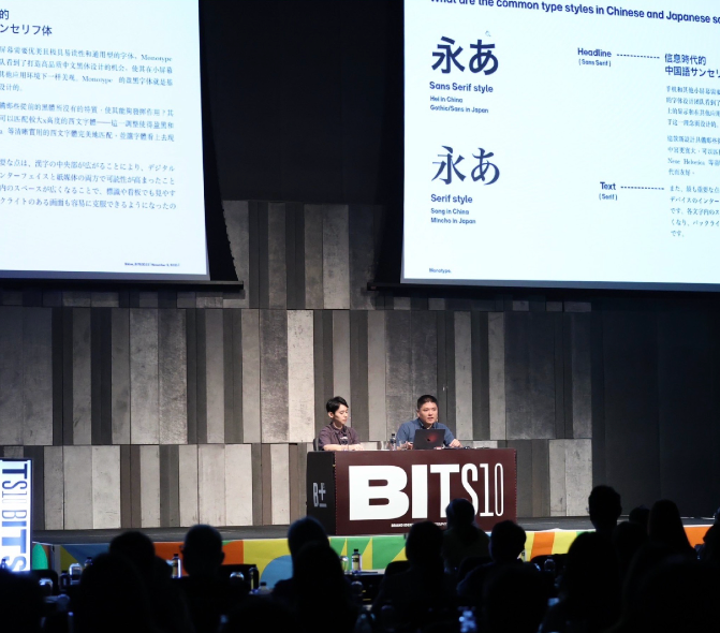
立足本地,放眼全球:蒙纳出席 BITS10,展示跨国品牌字体战略与知识
在 2023 年 11 月 2 日至 4 日举行的曼谷国际字体研讨会(BITS10)上,全球领先字体及技术专家蒙纳成为焦点。 BITS10 吸引了来自世界各地的 250 多位参与者,包括行业领导者、品牌创意人士、字体设计师和技术创新者。
分别代表蒙纳日本和中国的设计师土井辽太(Ryota Doi)和陶帝,以及蒙纳子公司 Fontworks 的森田俊也(Shunya Morita)进行了演讲。 他们分享了日本和中国字体趋势的最新见解,和为全球品牌打造本地化字体的专业知识;强调了中国对于展现优雅的书法字体的偏好,而日本则倾向于将平假名、片假名和表意文字相融合,并搭配流畅的无衬线字体。
他们也分享了企业字体在面对本地化需求时如何保持全球品牌策略的一致性。土井和陶帝展示了长城汽车、小米和普利司通的成功案例。
蒙纳为中国长城汽车开发了一款名为 GWM Sans 的定制字体,该字体融合了拉丁和中文字符,有助于增强用户在人机界面(HMI)上的交互体验。蒙纳还为跨国科技公司小米设计了泰语、老挝语和九种印度语字型,让小米更容易为全球用户提供本地化服务。 普利司通是轮胎行业的全球领导者,他们与蒙纳合作,定制了本地化字体,以确保分公司能够建立一致的国际品牌形象。
Fontworks 的字体设计师森田俊也(Shunya Morita)分享了他为即时通讯平台 LINE 开发企业字体的经验, LINE 在日本和其他亚洲国家得到广泛使用。他详细解释了如何创建与其原始英文版本完美匹配的日语字体,以确保用户获得舒适的双语体验。
蒙纳字体创意总监小林章(Akira Kobayashi)表示:“蒙纳致力于创造能够跨越文化和语言障碍的企业字体,为实现全球化品牌策略提供强大工具。”
随着东南亚本地品牌的崛起和跨国公司在当地市场的扩张,企业对字体及品牌解决方案的需求也日益增长。 蒙纳致力于扩大其字库和合作伙伴网络,以满足多样化的客户需求,创造令人难忘的品牌体验。